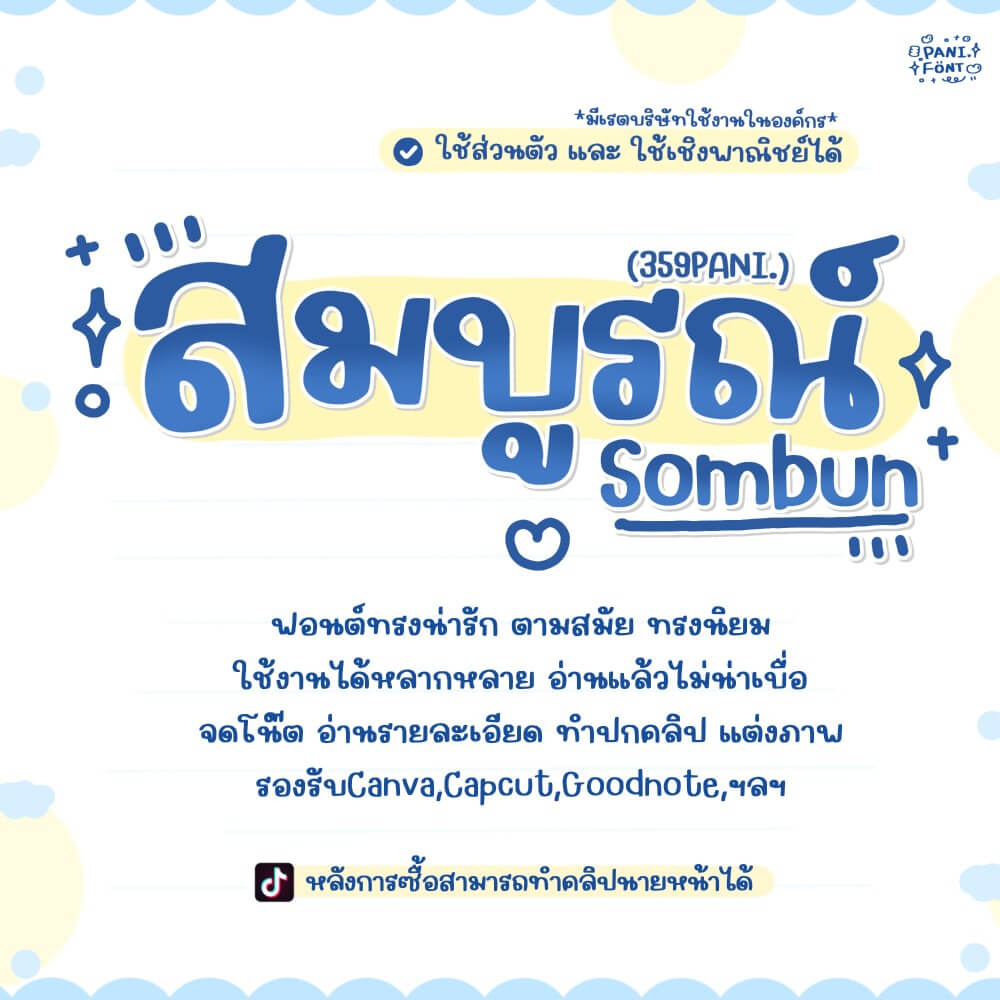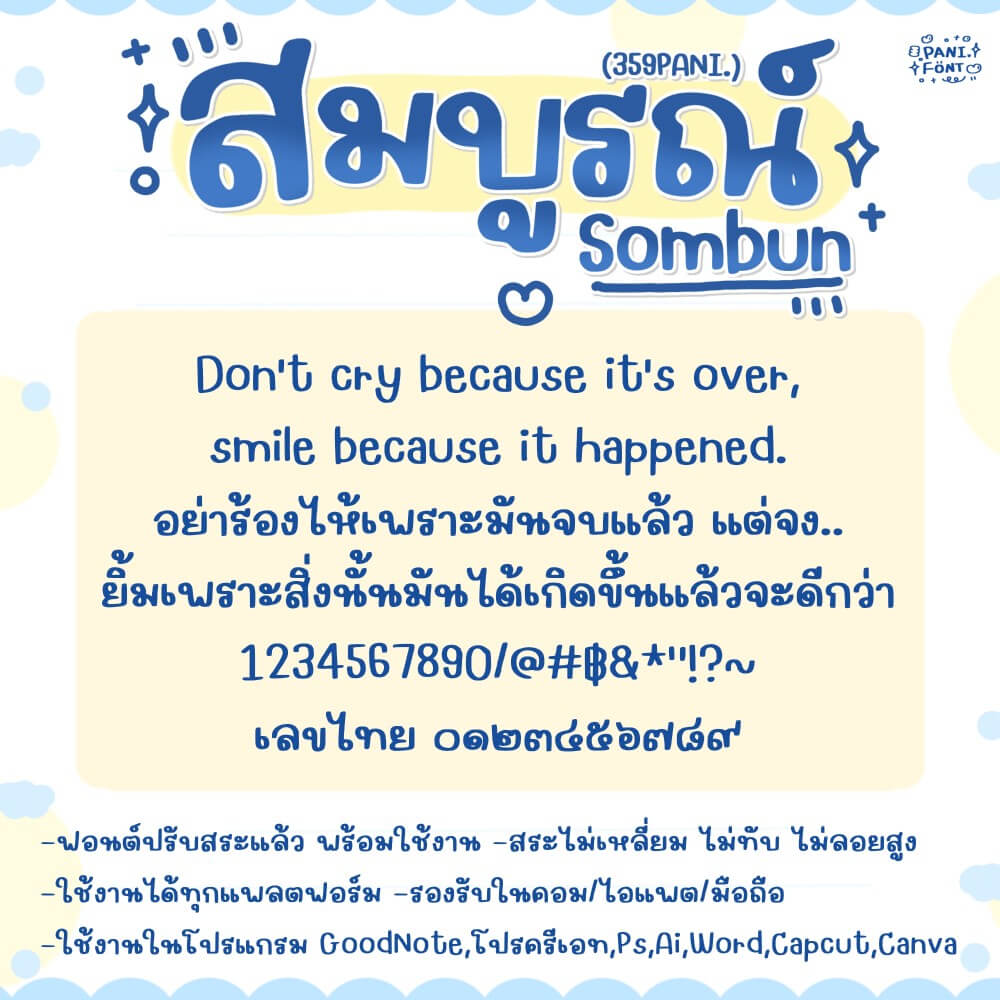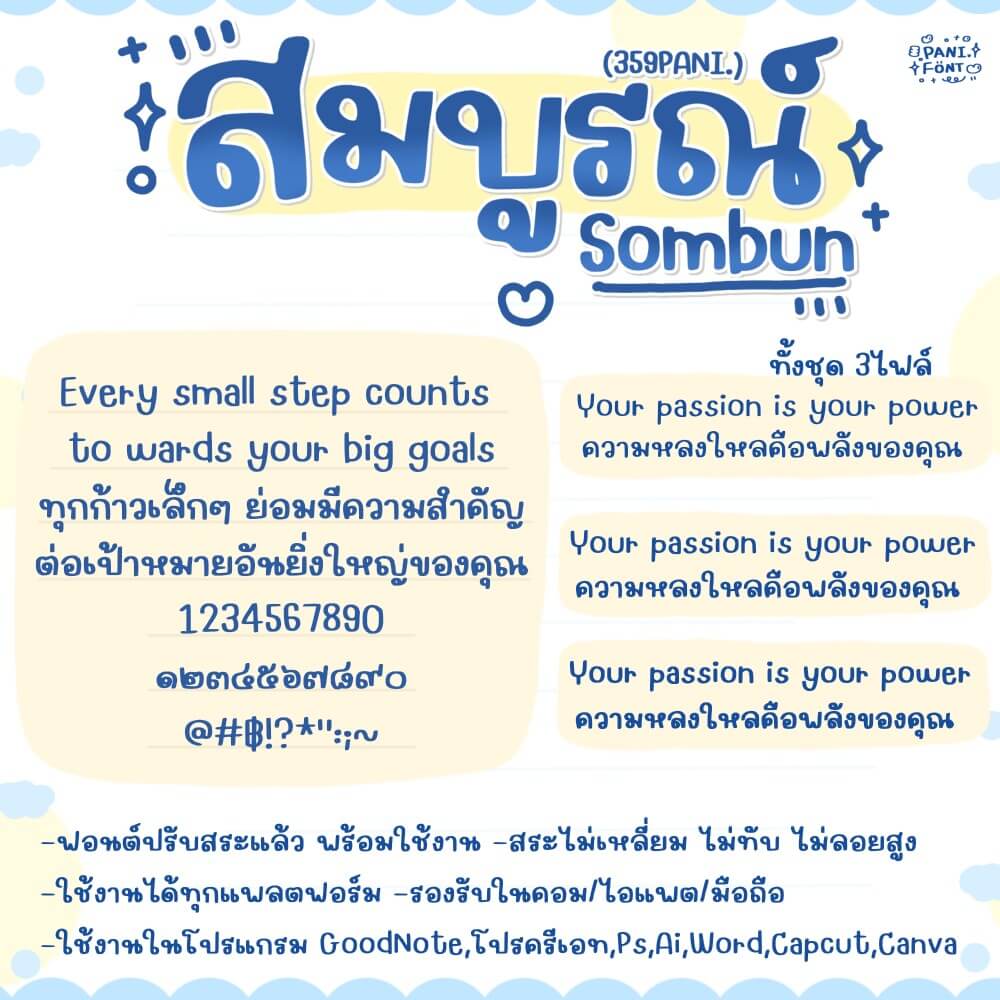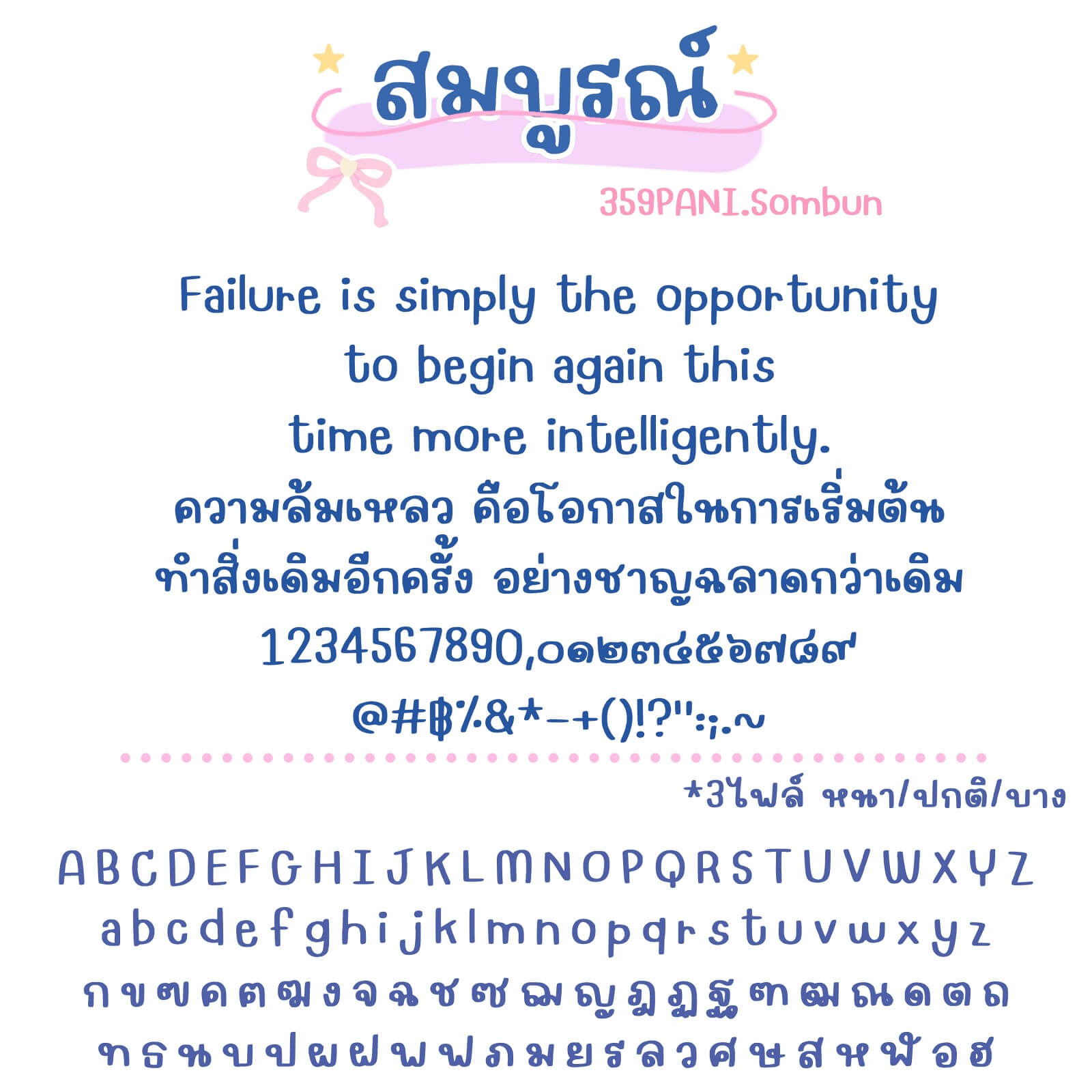
ฟอนต์ 359PANI.สมบูรณ์ – ฟอนต์ทรงน่ารัก ตามสมัย ทรงนิยม ใช้งานได้หลากหลาย อ่านแล้วไม่น่าเบื่อ จดโน้ต อ่านรายละเอียด ทำปกคลิป แต่งภาพ
เหมาะกับมือใหม่ตัดคลิป
359PANI.สมบูรณ์